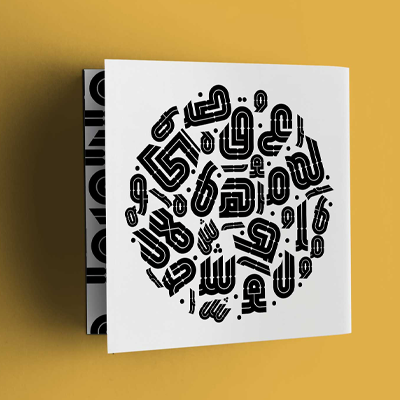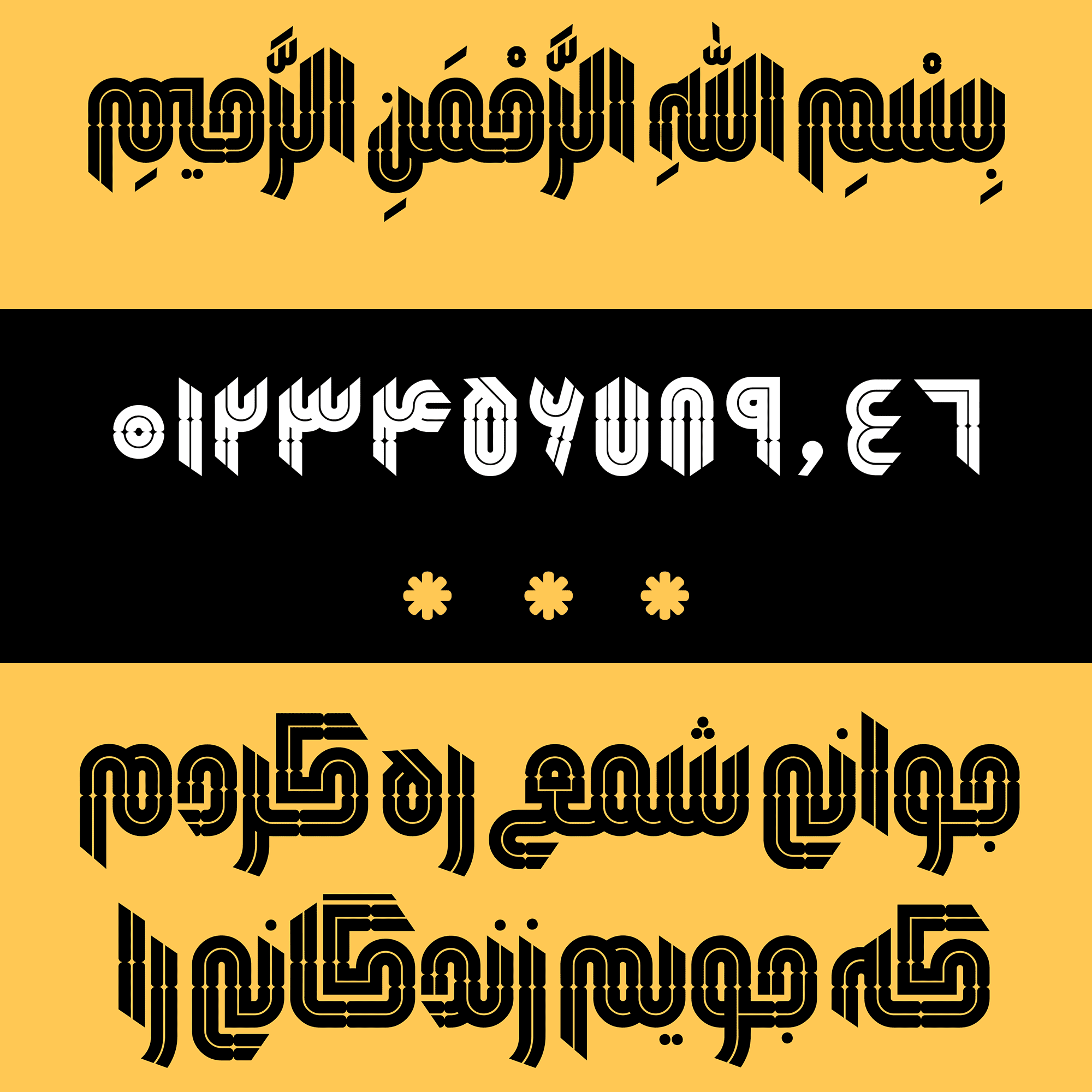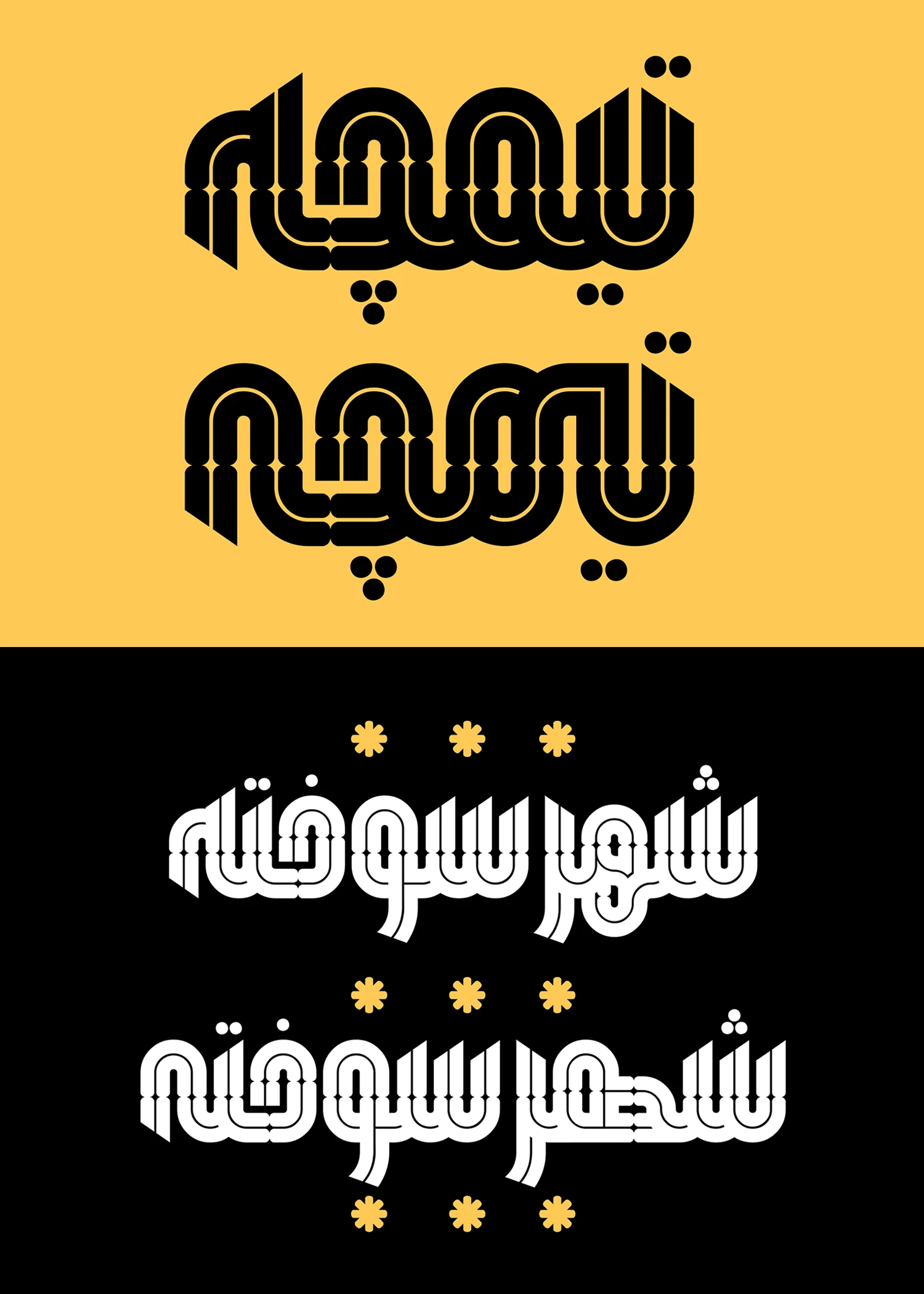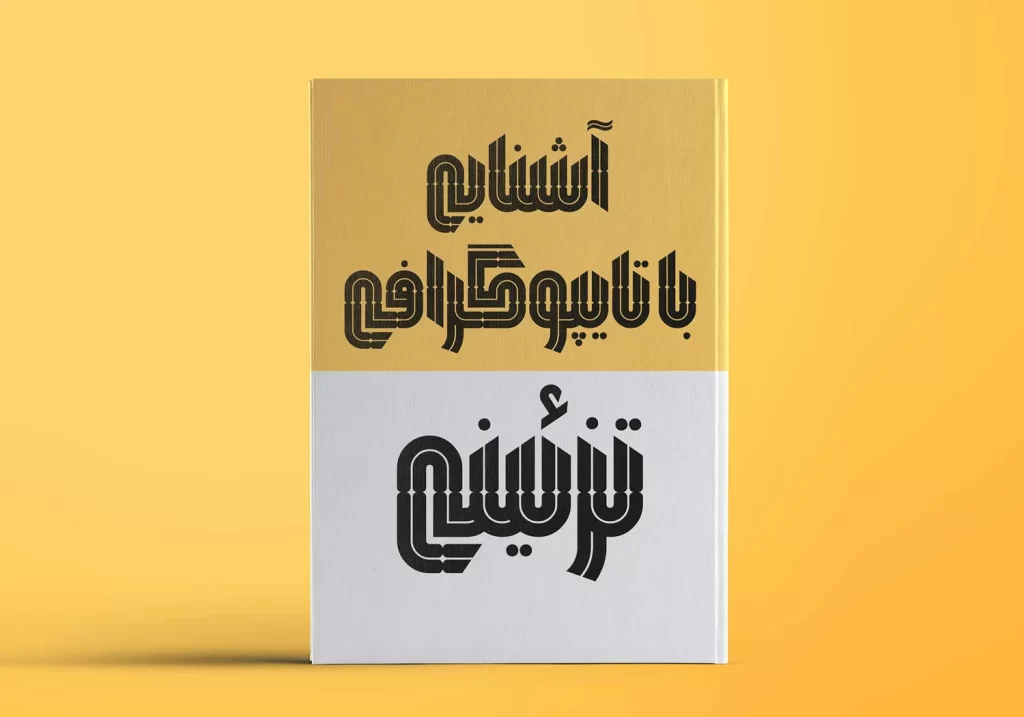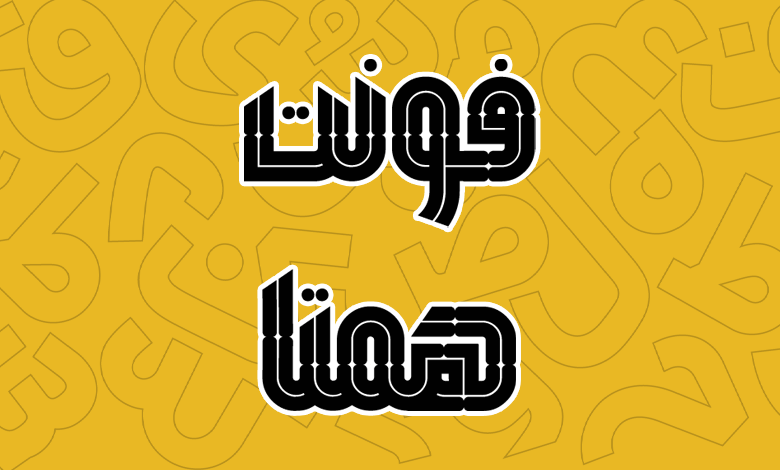
فونت همتا (Hamta)
فونت همتا (به انگلیسی: Hamta) در دسته فونتهای عنوان، فانتزی و مناسب تبلیغات قرار دارد که در یک وزن معمولی Regular طراحی و با فرمت TTF در دسترس است. اگر به دنبال یک قلم مناسب با ساختار اینلاین هستید که با تلفیقی از خط کوفی و ساختاری هندسی طراحی شده باشد این قلم را به شما پیشنهاد میکنیم.
قلم همتا توسط وحید یعقوبلو طراحی شده است که پیش از این قلم دیگری با نام فونت یکتا را از این طراح تایپفیس معرفی کردهایم که در همین سبک بوده و نشان از تبحر این طراح در طراحی قلمهای فانتزی، تزئینی و نمایشی دارد. امین عابدی نیز توسعه این قلم را برای استفاده در محیط نرمافزار برعهده داشته است.
در طراحی فونت تزئینی همتا از خط کوفی تزئینی استفاده شده که با تلفیقی در کنار ساختار هندسی، شکل اینلاین (درون خطی) برای تمام حروف این قلم در نظر گرفته شده است. این قلم با هدف استفاده در مواردی که لزوما نیازی به بودن خوانایی زیاد نیست طراحی شده است که برای همین مناسب متنهای طولانی نیست و میتواند برای مواردی مثل عناوین و تیترها کاربردی باشد.
از این قلم میتوان در طرحهای گرافیکی فرهنگی استفاده کرد که با ترکیب شدن در کتیبهها میتواند خروجی عالی از نظر طراحی را ارائه کند. یا اینکه برای صنعت چاپ در طراحی جلد کتب فرهنگی و هنری از آن استفاده کرد.
تلفیقی از خط کوفی و هندسی با وزن معمولی
فونت همتا با ترکیبی از خط کوفی تزئینی و شکل دادن به این خط در قالب ساختاری هندسی طراحی شده است که دارای یک وزن معمولی Regular است. این قلم صرفا از فرمت TTF پشتیبانی میکند که برای استفاده در انواع سیستم عامل و نرمافزارهای گرافیکی و ویرایشگر متن قابل استفاده است.
امکانات این قلم مثل حروف جایگزین و استفاده از کاراکترها و سمبلهای خاص هر زبان با استفاده از تنظیمات OpenType در دسترس هستند که میتوانید به شکلی خلاقانه در طرحهای گرافیکی خود از آنها بهره ببرید.
پشتیبانی کامل از زبان فارسی و عربی
قلم همتا از آنجایی که بر اساس خط کوفی طراحی شده صرفا از دو زبان فارسی و عربی پشتیبانی میکند و بر خلاف بسیاری از فونتهای دیگر، خبری از پشتیبانی این قلم از زبان انگلیسی یا سایر قلمها نیست.
هر دو این زبانها دارای رسم خط یکسانی بوده و صرفا برای زبان عربی در برخی حروف مثل «ک، ی، ه، ؤ، ئ» و اعداد «۴۵۶» تفاوت جزئی وجود دارد که توسعهدهنده این قلم برای ایجاد یک قلم استاندارد برای هر دو زبان این موارد را رعایت نموده است.
در این قلم میتوانید از حروف، اعراب و اعداد هر زبان در کنار کاراکترهای خاصی که وجود دارد استفاده کنید تا خروجی استانداردی داشته باشید.
دارای حروف جایگزین و نمایشی
ویژگی متمایز کننده دیگر قلم همتا پشتیبانی از حروف جایگزین است؛ حروفی که چه در ابتدا، چه در میانه و چه در انتهای کلمات قرار بگیرند، دارای چند سبک نوشتاری مختلف هستند که همین مسئله کمک میکند بتوانید کلماتی که شامل این حروف هستند را در چند حالت مختلف تایپ کنید.
به عنوان مثال همانطور که در تصویر زیر مشاهده میکنید، طراحی ترکیبهای «ـمـ، ـیـ، ـه» در این قلم دو ساختار متفاوت را فراهم میکند که امکان تایپ کلمهای همچون «تیمچه» را در دو شکل متفاوت دارید.
یا در نمونه دیگری حرف «ه» در میانه کلمات را مشاهده میکنید که در دو ساختار متفاوت به صورت «هـ، ـهـ» تایپ میشوند و کلمهای مثل «شهر» را در دو ترکیب برای ما نمایش خواهند داد.
فونت تزئینی و نمایشی مناسب برای عناوین
ساختار قلم همتا تزئنی و نمایشی است. از این فونت میتوانید در انواع زمینهها مثل تبلیغات، چاپ جلد کتب و دیگر موارد استفاده کنید که شکل و ساختاری نزدیک به خط کوفی را برایتان فراهم خواهد کرد.
خصوصا اینکه اگر بهدنبال قلمهای با حروف اینلاین هستید، میتوانید این قلم را با دیگر فونتها نظیر فونت سپید و فونت امکان ترکیب کنید که علاوه بر سایر وزنها، یک وزن اینلاین هم دارند.
از این قلم میتوانید برای طراحی انواع بنر، تصاویر شبکههای اجتماعی و اسلایدر در سایت با هدف طرحهای فرهنگی و اسلیمی استفاده کنید که نیاز به یک قلم اینلاین با تلفیقی از خط کوفی و ساختاری هندسی دارید.